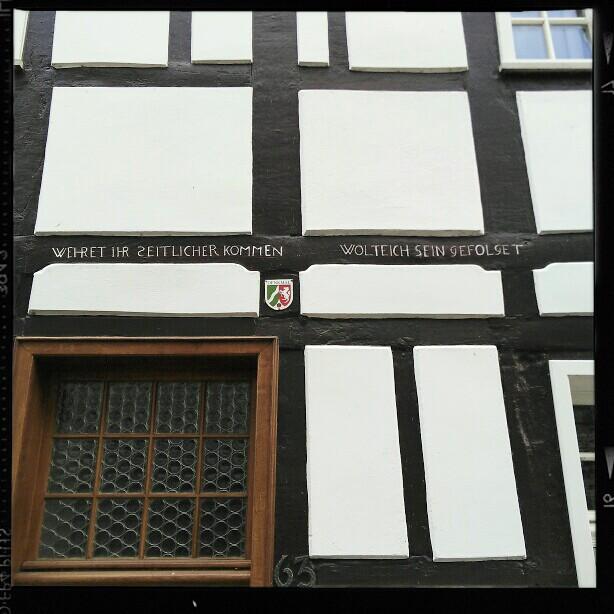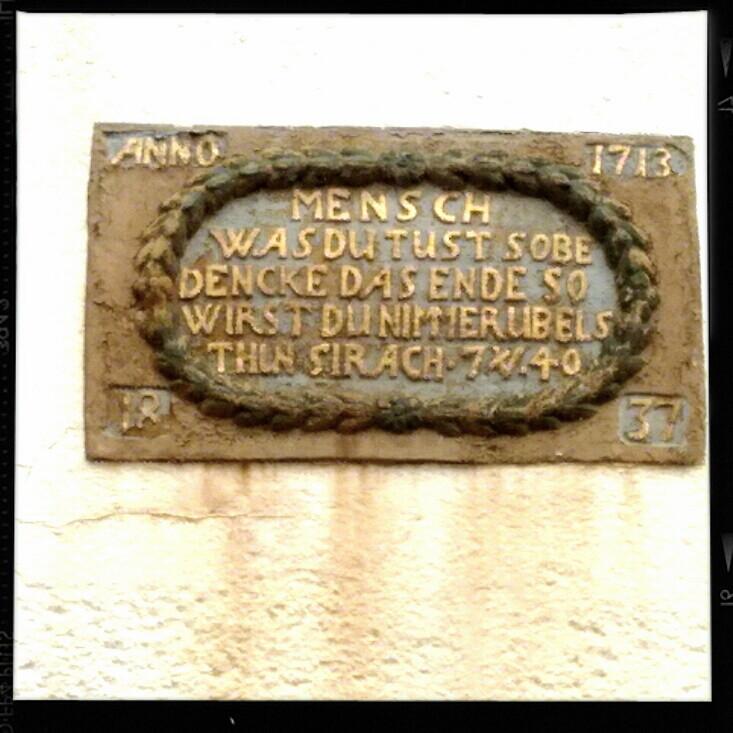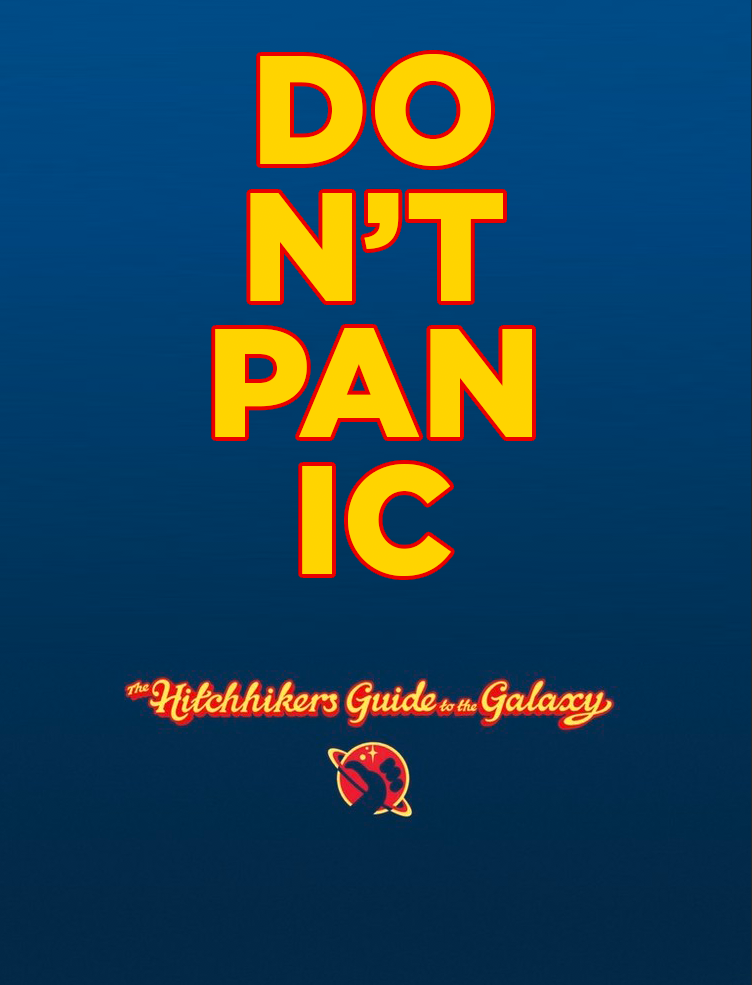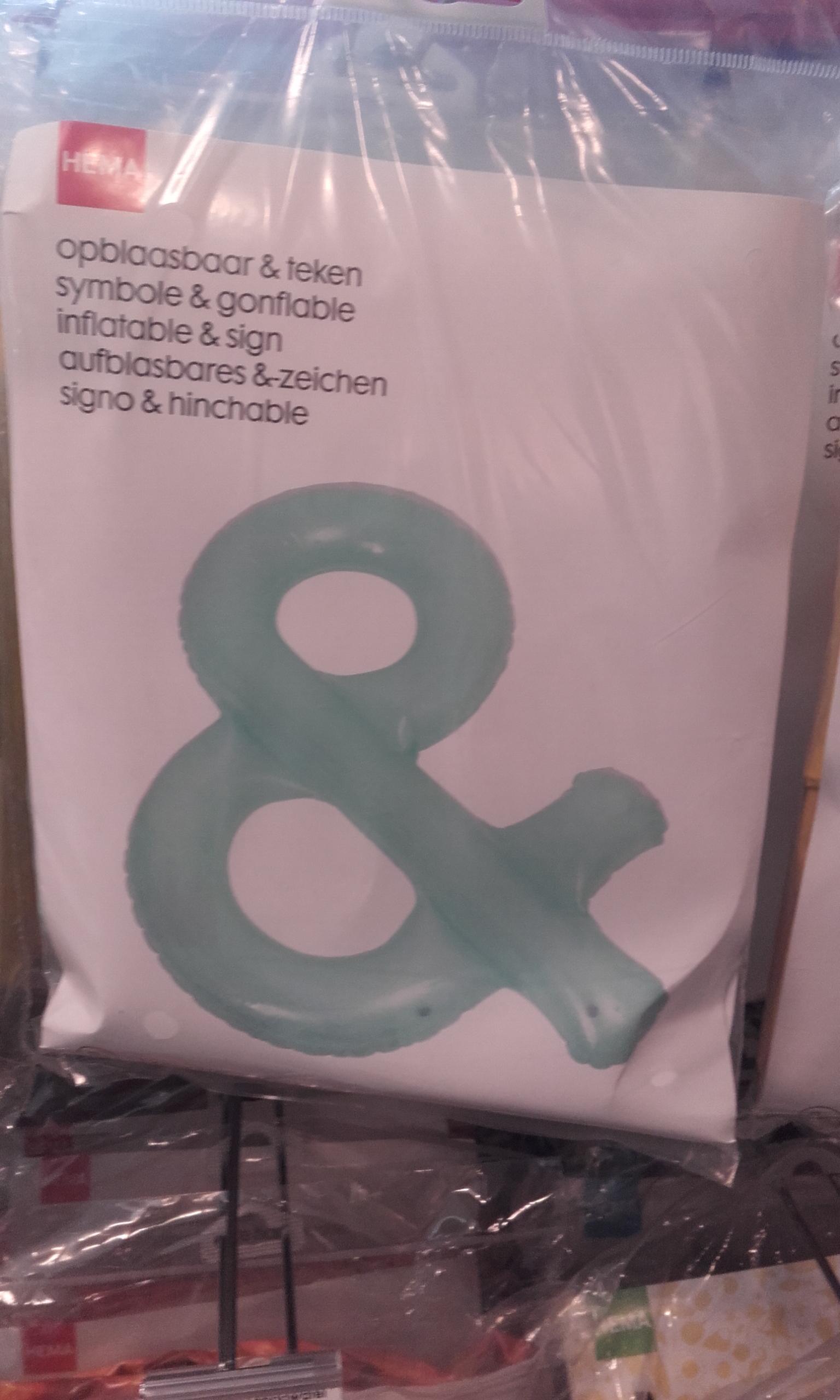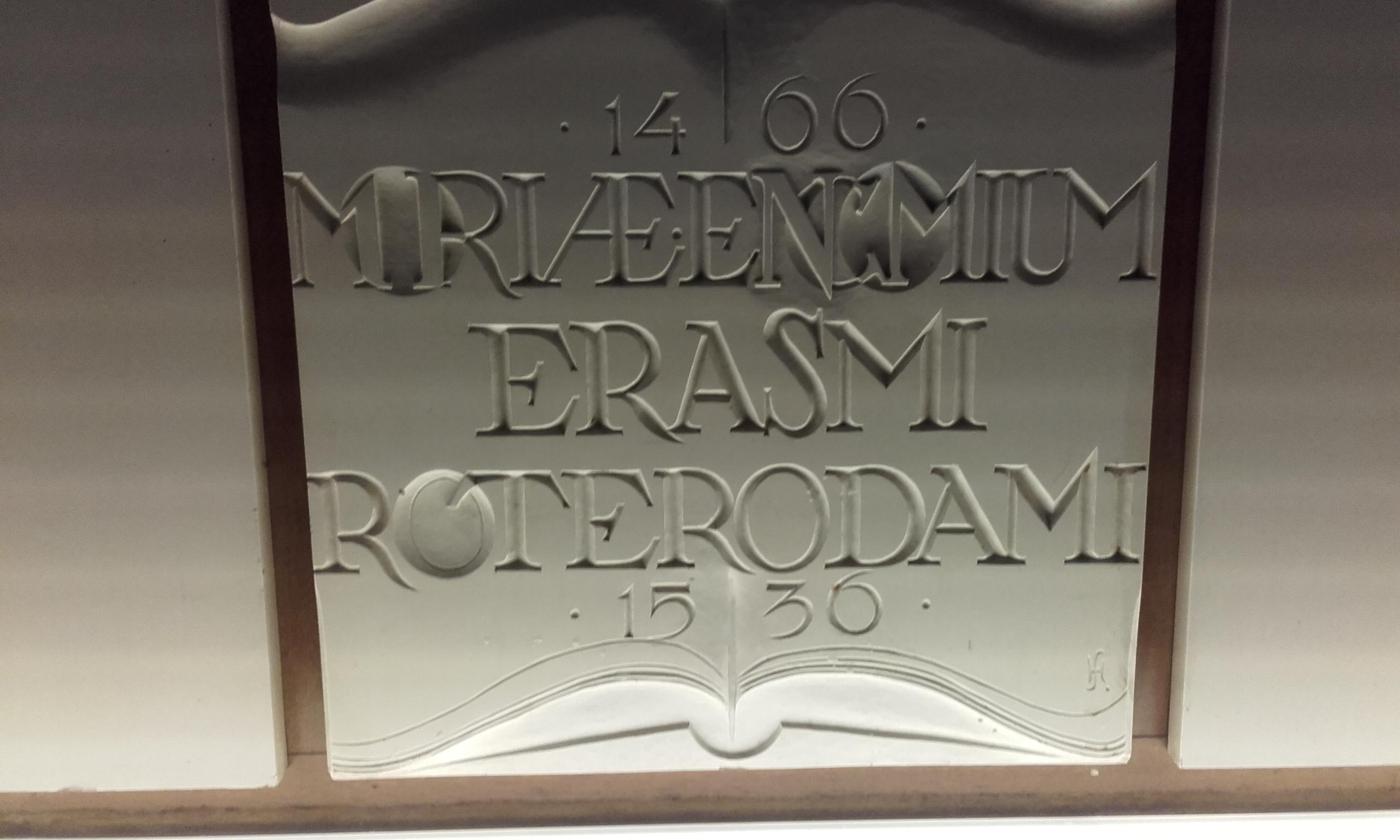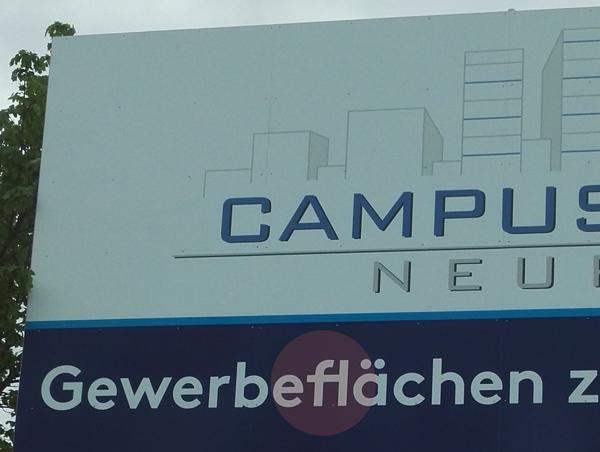
Im Buchladen bei uns hat ein Vertreter (?) von Marco-Polo versucht, das der Buchhändlerin wie folgt zu erklären: „Wenn man in Paris in einem Café sitzt und der Kellner sieht das Heft, wo Pa-Ris drauf steht, dann stutzt der erst einmal und dann kann man erklären, dass man aus Deutschland kommt und schon hat man ein Gespräch“
Die Buchhändlerin hat ihm das nicht geglaubt. Warum nur?
Weil sie naiv war? :-?;-):-D
Warum haben die eigentlich dann  nicht auch die Marke angepasst:
MAR
COP
OLO
Oder wirbt bei denen ein Laptop-Händler für seinen Hamburger Laden, und hat die damit auf die Idee gebracht?
Mal gucken ob ich hier Touristen mit einem Führer mit
GE
RM
ANY
oder
NOR
DSEE
Dann hätte man ja wenigstens schonmal was zum Reden …
Warum nur?
Weil die Vorstellung, Pariser Kellner würden an Gesprächen mit Touristen interessiert sein, einfach zu absurd ist. :!:
Hallo zusammen, habe ich in München gefunden,
wahrscheinlich hab ich damals an der FH wieder mal nicht richtig aufgepasst gehabt in
Typografie ... ist das eine (gelungene) Ligatur? Oder für was ist der horizontale Strich?
PS: Gemeint ist das rot Eingekreiste ...
... ist das eine (gelungene) Ligatur?
:nicken::roll:
Rechtschreibung: 'opblaasbaar', aber 'opblaasbare'.
Hier auf der Verpackung ist 'opblaasbaar' die richtige Form.
Du hast das Wort nur etwas aufgeblasen. Ist doch auf seine eigenen Weise OK.
Ab wie viel a's knallt's? *ohrenschonmalzuhalt*
Ab wie viel a's knallt's?